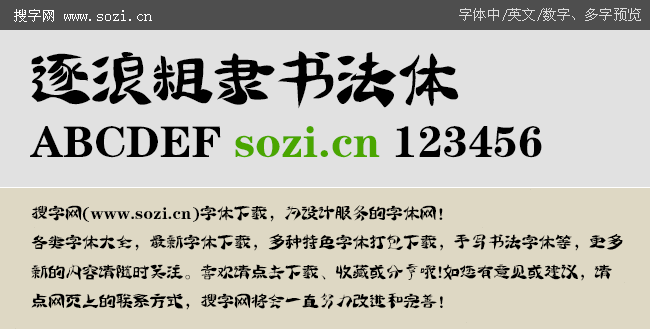
逐浪粗隸書法體
搜字網(wǎng)提供一款逐浪粗隸書法體中文書法字體下載,逐浪粗隸書法體是一款手寫風格的個性化書法字體,該字體整體效果十分出色,適合應用于廣告設(shè)計、名片設(shè)計、包裝印刷、產(chǎn)品設(shè)計等應用。(逐浪字庫如需商用授權(quán),請聯(lián)系:0791-86161900 QQ:404655890)